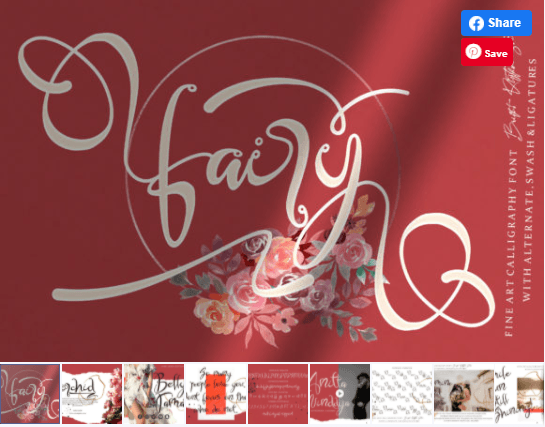
Fairy Font
Fairy - это шикарный утонченный шрифт, излучающий изысканность и элегантность. Его стильные альтернативы и лигатуры делают этот шрифт идеальным для любого проекта. Fairy имеет кодировку PUA, что означает, что вы можете легко получить доступ ко всем глифам и росчеркам!